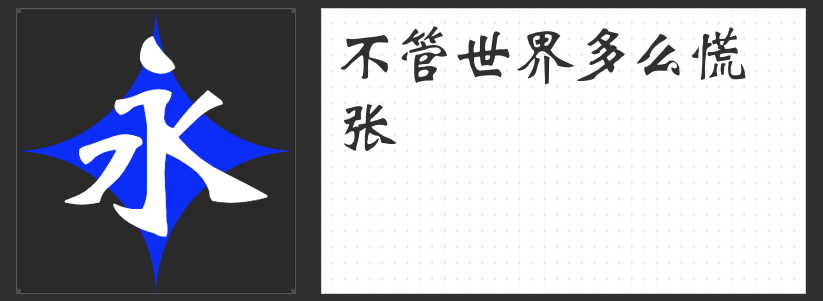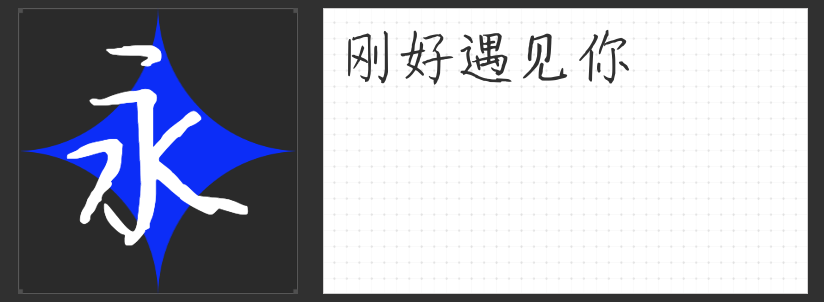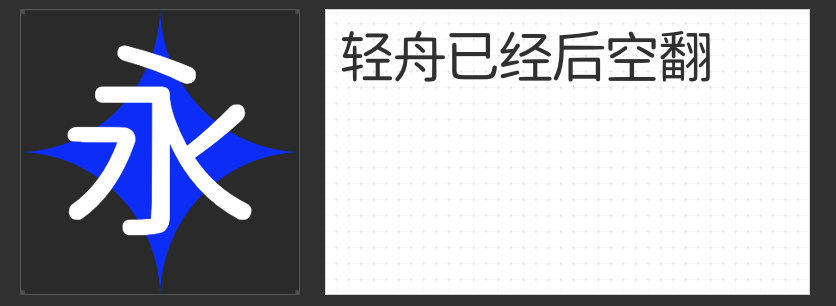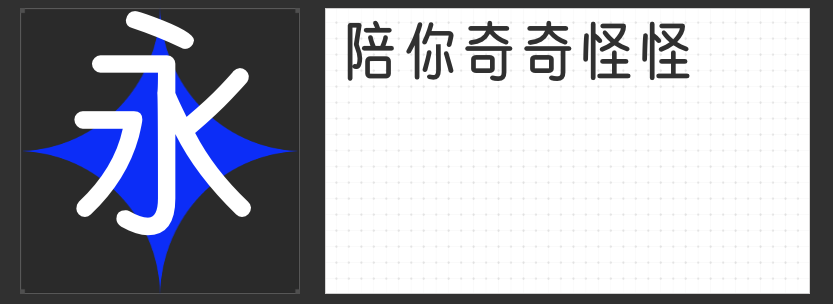
四款怀旧风字体推荐:让设计穿越时光,唤醒记忆的温度
在设计中融入怀旧元素,不仅能传递情感共鸣,更能赋予作品独特的岁月质感。以下四款字体,或源于铅字印刷的工艺痕迹,或承袭传统书法的气韵精髓,皆能以细节之美唤醒旧时光的温情。
一、字圈也字幼稚黑体
这款黑体的独特之处,在于笔画端口的“喇叭口”装饰——这一设计源于早期铅字印刷的技术局限。受限于油墨扩散与模具收缩,工匠们创造性地将笔画末端设计为外扩形态,既弥补了印刷缺陷,又意外赋予字体灵动的装饰感。
二、云书法硬笔颜楷简
以颜真卿书法为根基,这款硬笔楷书将传统书法的磅礴气韵与现代印刷的简洁需求完美融合。用笔洒脱却不失法度,字形方整而点画硬朗,撇捺舒展如长枪大戟,在规整中暗藏灵动。其怀旧感并非刻意模仿古旧,而是通过颜体独有的“筋骨”传递出一种历经岁月沉淀的从容——既适合表现古典文化的厚重,也能为现代设计注入一份沉稳的文人气质。
三、励字魏体简繁
魏碑的雄浑与印刷体的规整在此碰撞出火花。这款字体将魏碑的结体特点进行标准化处理,点画刚劲如刀刻,收笔方圆兼施,行笔轻重交错,仿佛将北魏碑刻的苍劲之力凝练于笔画之间。其结构紧密而内敛,笔法丰富却隐而不露,既有金石铭文的古朴厚重,又不失现代字体的易读性,适合需要传递历史感与力量感的设计场景。
四、字圈也字万能黑体
同样的圆体字体,把笔画全部变圆角处理,在细节上更显克制与优雅。它保留了黑体的方正基调,通过微妙的圆润弧度,让字体在严肃中透出一丝俏皮。这种“复古未来主义”的设计哲学,恰似对铅字时代的温柔致敬——既是对工艺局限的超越,也是对设计本源的回归。
这四款字体,或承载技术演进的历史,或延续书法美学的血脉,皆能为设计注入超越时间的怀旧氛围。让文字成为时光的容器,唤醒观者心底那份柔软的记忆。